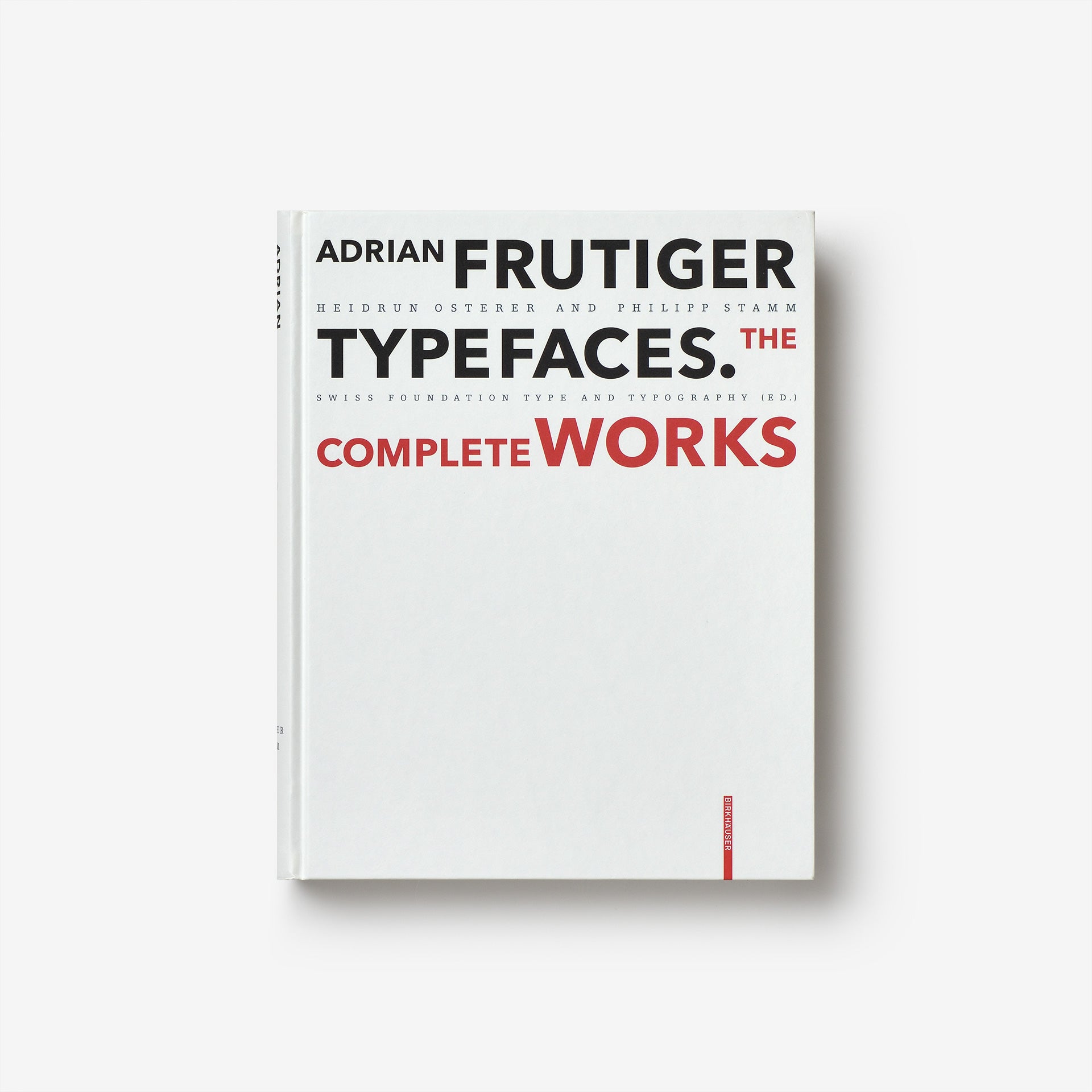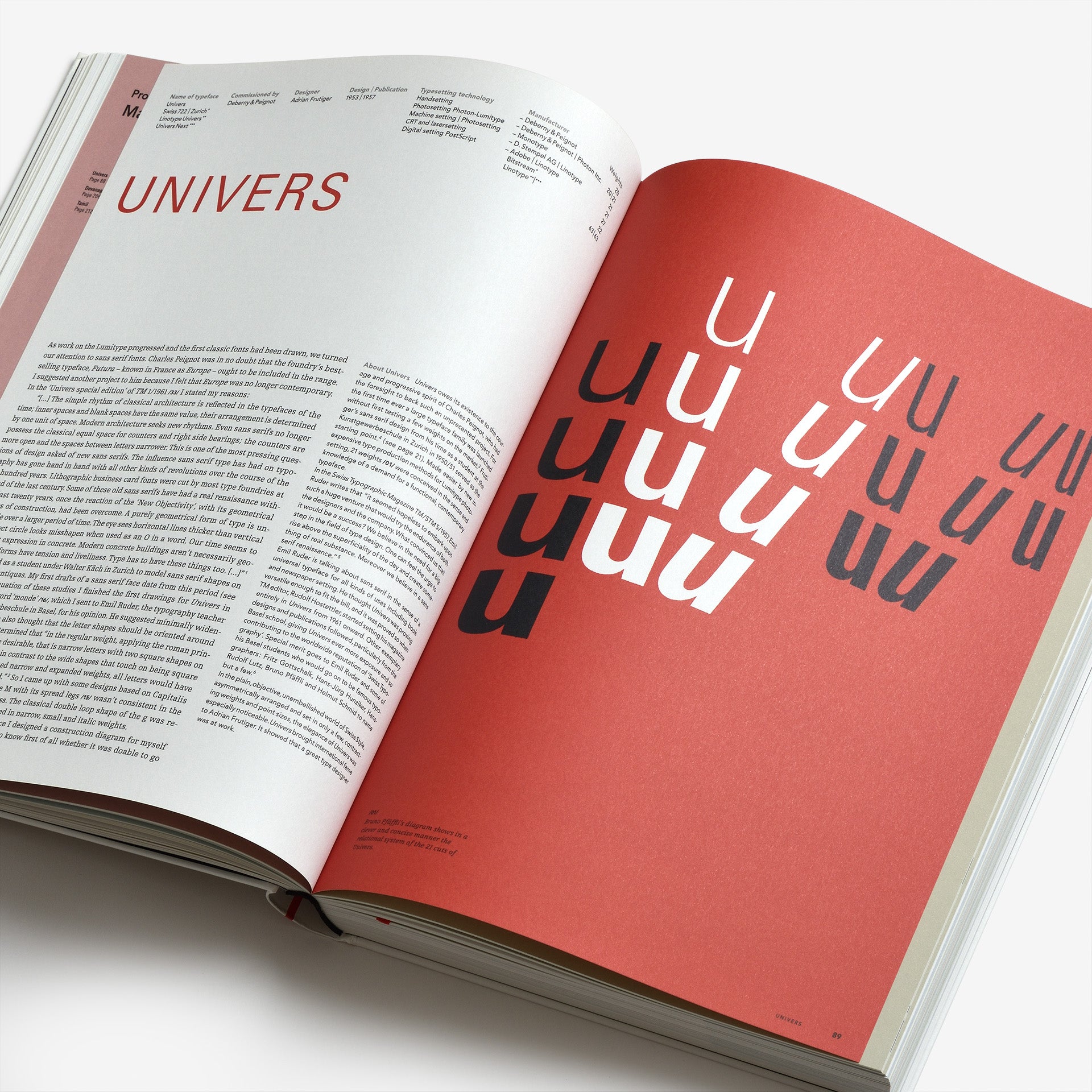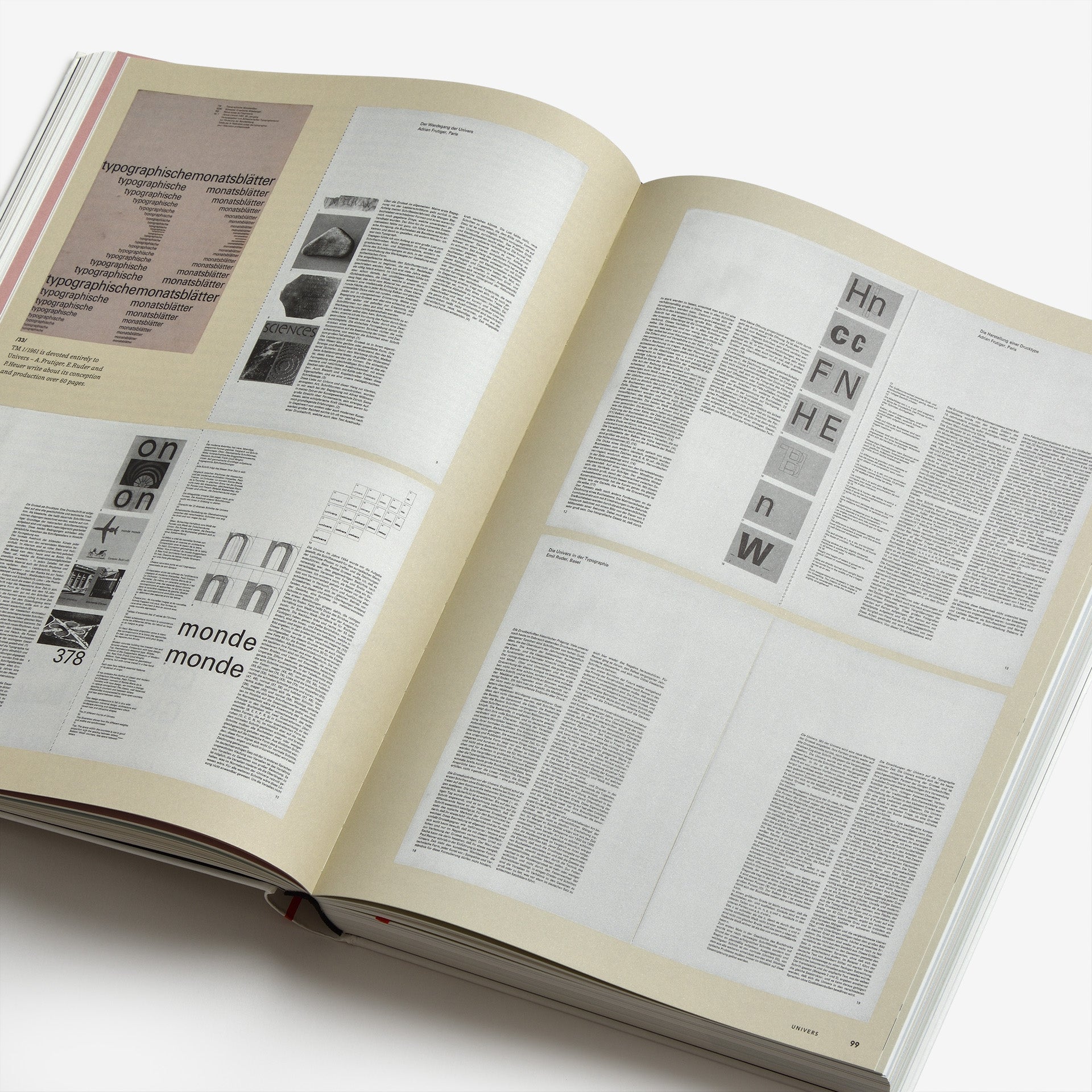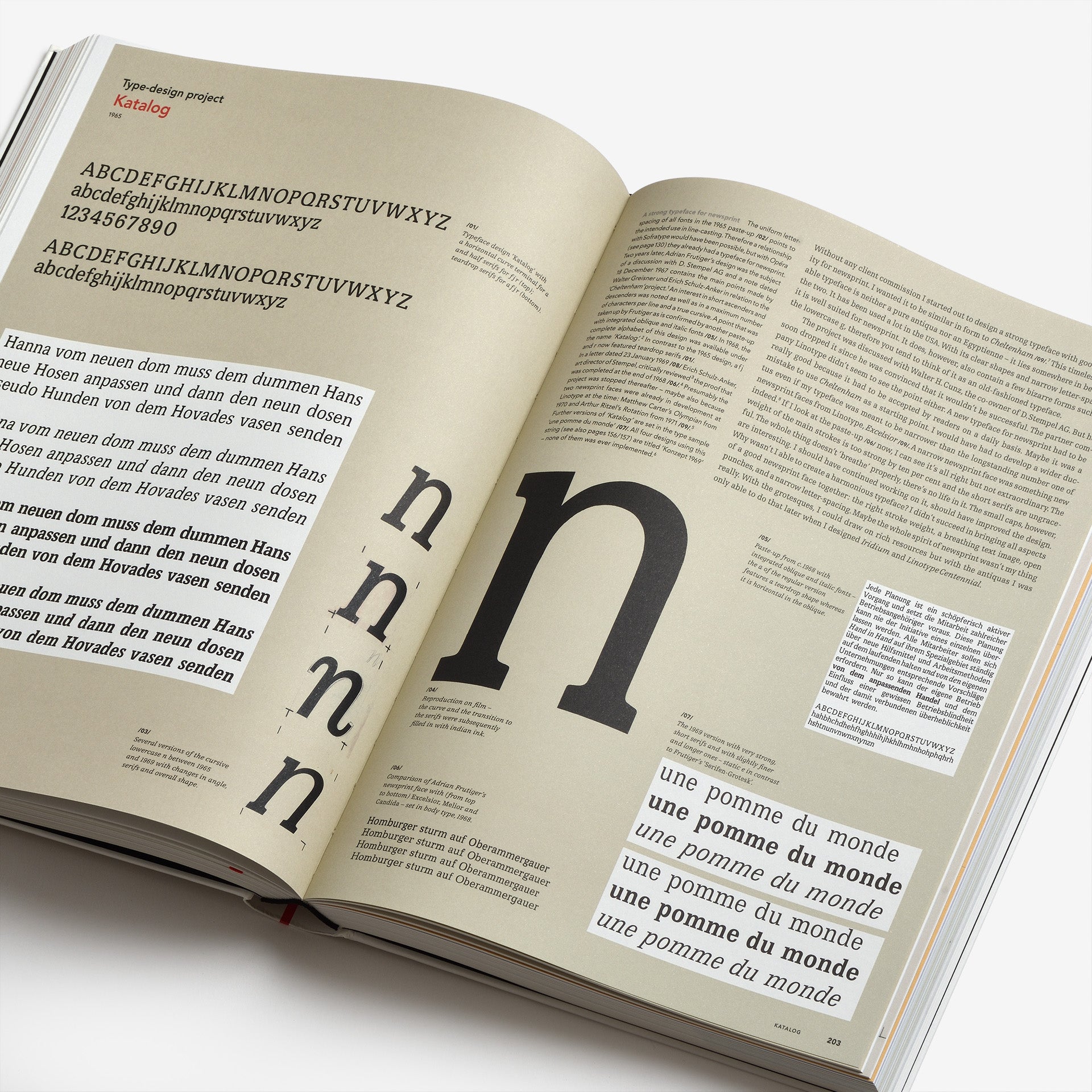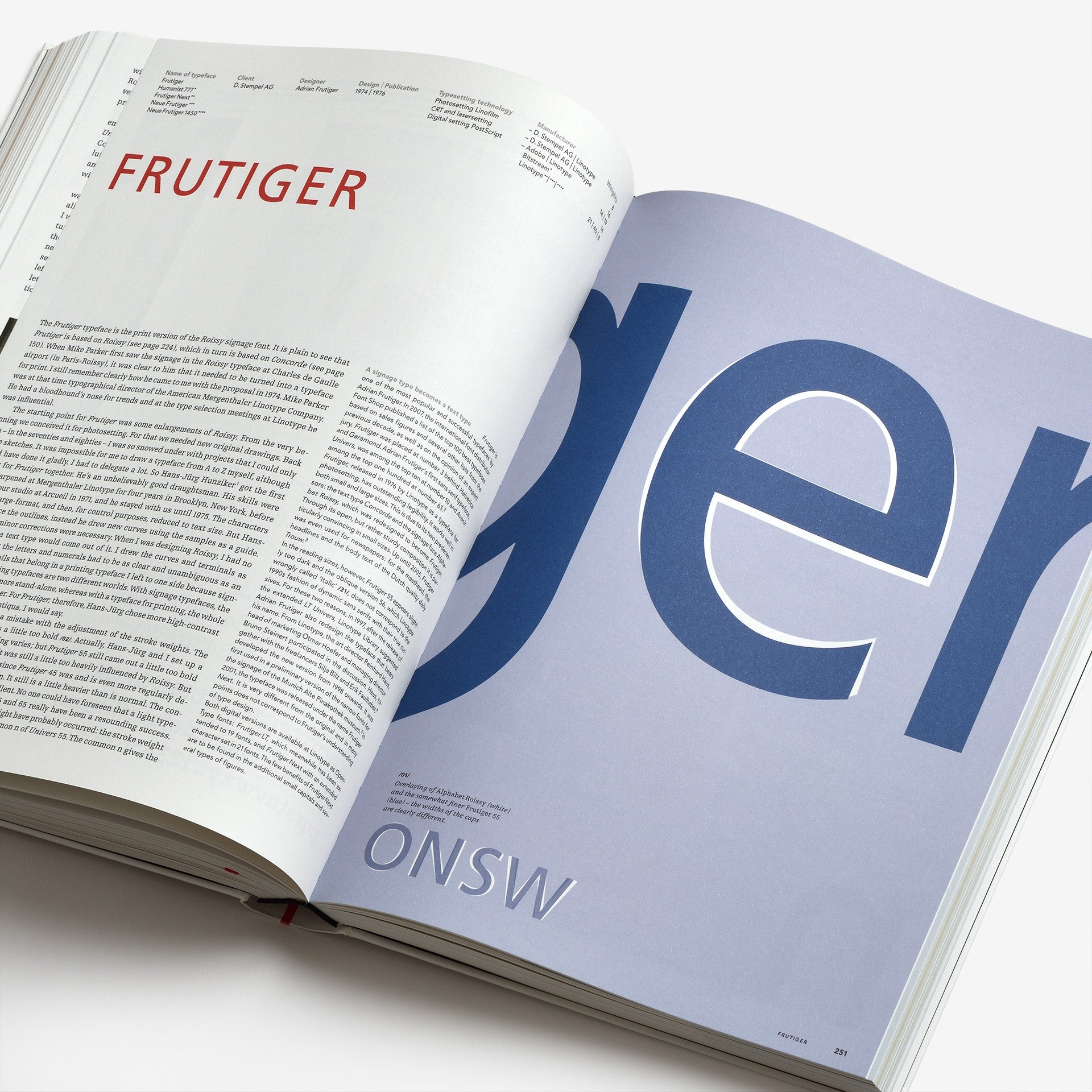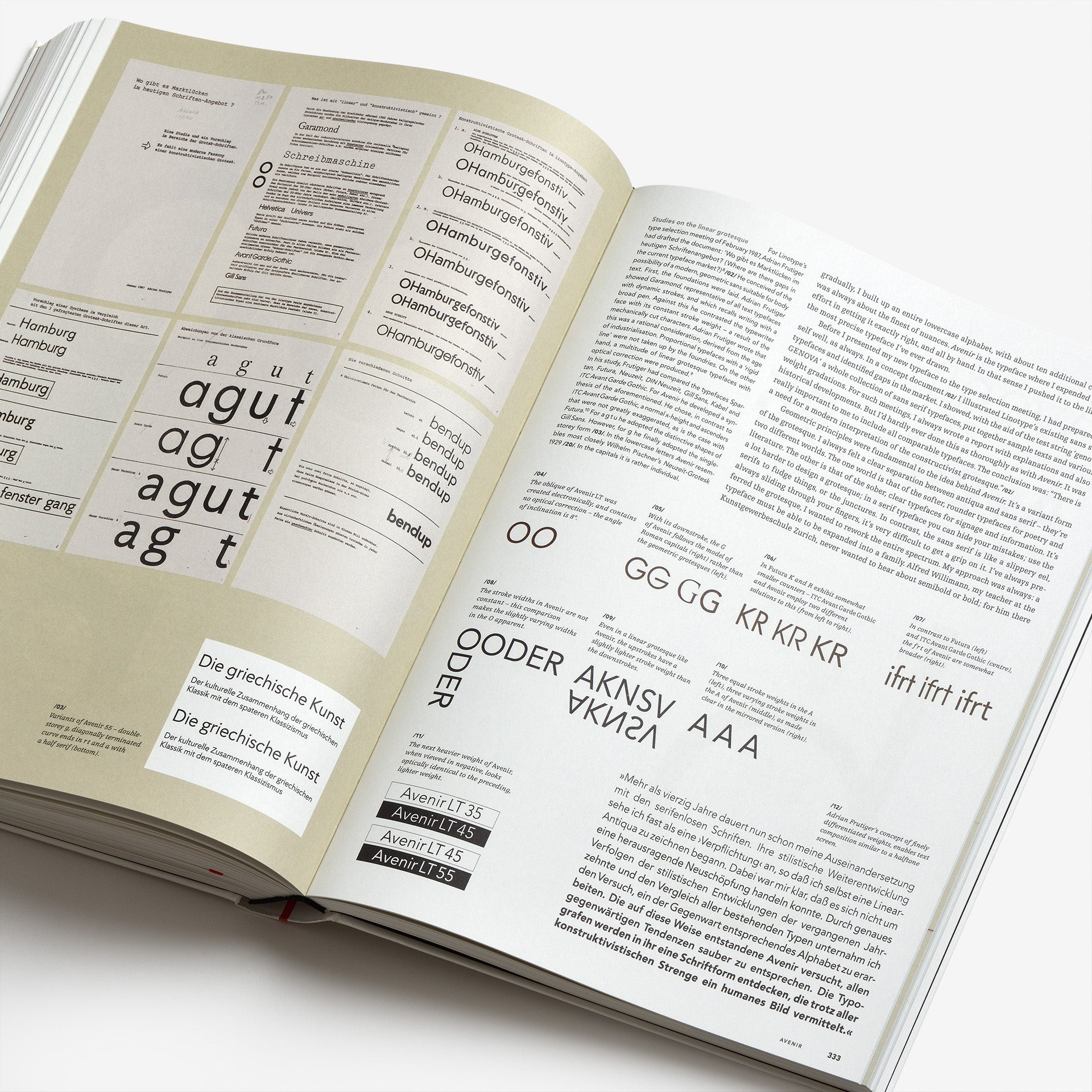
Adrian Frutiger – Typefaces: The Complete Works
スイスの書体デザイナー、アドリアン・フルティガー(Adrian Frutiger)の作品集。1950年以降の国際的な書体の作成は、フルティガーに大きな影響を受けています。「Univers」やISO規格に採用された書体「OCR-B」は画期的であり、パリ空港のための書体は標識用書体の新しい基準となり、「Frutiger」へと発展していきました。また、コーポレートフォントでは、日本の資生堂の化粧品ラインなど、企業の公共的なプロフィールを定義するのに貢献しました。「Ondine」や「Méridien」、「Avenir」、「Vectora」など約50種類もの書体を制作しました。
本書は、フルティガー本人との対話、フランス、イギリス、ドイツ、スイスでの徹底的な取材をもとに、この書体デザイナーの芸術的成長をきわめて詳細かつ正確に記録しています。デザインから販売に至るまで、フルティガーが手がけたすべての書体を初めて図版化し、技術や関連する書体を参照して分析されました。また、未発表の書体や100点以上のロゴマークも掲載されています。